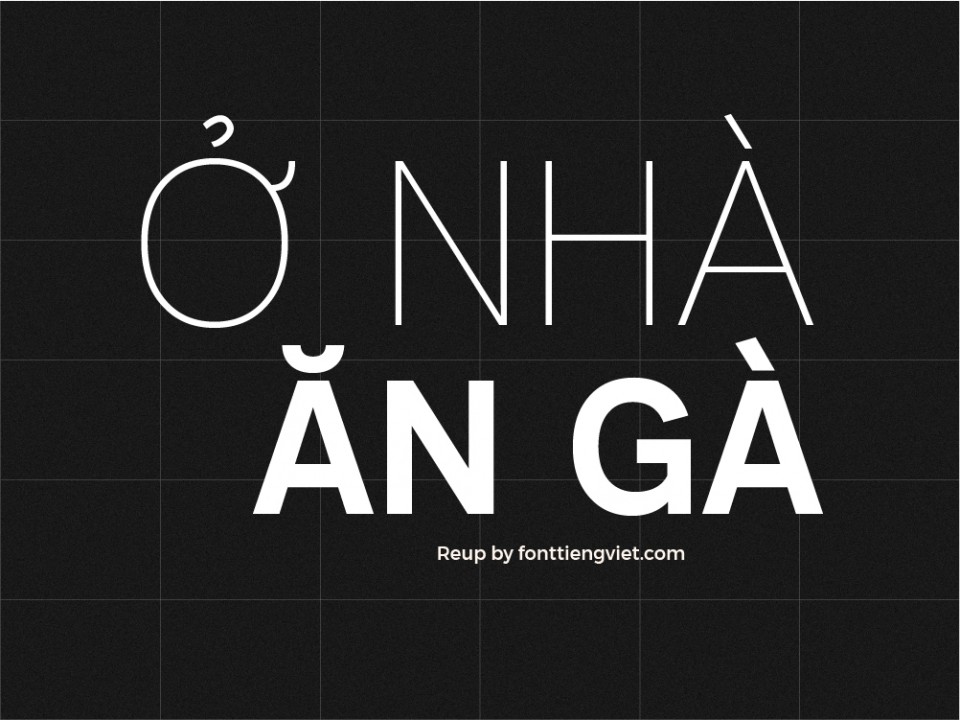
Tải Ngay Bộ Font việt hóa iCiel Novecento ( 6 font ) Sang Trọng Và Đẳng Cấp
Giới thiệu về bộ Font việt hóa iCiel Novecento ( 6 font )
Trong thế giới thiết kế đồ họa hiện đại, việc tìm kiếm một bộ Font Chữ vừa mang nét cổ điển vừa giữ được sự tinh tế là điều không hề dễ dàng. Bộ Font việt hóa iCiel Novecento ( 6 font ) chính là giải pháp hoàn hảo cho các nhà thiết kế tại Việt Nam. Đây là một bộ font thuộc phong cách Uppercase-only (chỉ có chữ hoa), được lấy cảm hứng từ những kiểu chữ hình học phổ biến ở châu Âu vào cuối thế kỷ XIX. Với cấu trúc cân đối và đường nét dứt khoát, bộ font này mang đến hơi thở của sự sang trọng, chuyên nghiệp cho mọi tác phẩm nghệ thuật.
Đặc điểm nổi bật của iCiel Novecento
Bộ Font việt hóa iCiel Novecento ( 6 font ) bao gồm sáu định dạng khác nhau từ Light đến UltraBold. Điều này cho phép người dùng linh hoạt thay đổi độ dày mỏng của chữ để phù hợp với từng mục đích cụ thể như làm tiêu đề sách, bìa tạp chí hay thiết kế logo thương hiệu. Điểm đặc biệt nhất là phiên bản này đã được iCiel Việt hóa hoàn chỉnh, hỗ trợ đầy đủ các dấu tiếng Việt một cách chuẩn xác, giúp các bạn học sinh và giáo viên dễ dàng ứng dụng trong việc trình bày bài giảng hoặc làm poster sự kiện trường học mà không lo lỗi font.
Ứng dụng thực tế của bộ font trong thiết kế
Nhờ tính thẩm mỹ cao, bộ font này thường xuyên xuất hiện trong các dự án quảng cáo cao cấp và thiết kế nhận diện thương hiệu. Sự tối giản nhưng mạnh mẽ của iCiel Novecento giúp truyền tải thông điệp một cách trực diện và ấn tượng. Đối với lĩnh vực giáo dục, bộ chữ giúp các biểu ngữ trở nên trang trọng và hiện đại hơn rất nhiều so với các kiểu chữ truyền thống. Bạn có thể kết hợp chúng với các font chữ không chân khác để tạo nên sự tương phản thú vị và lôi cuốn người xem.
Kết luận về bộ Font việt hóa iCiel Novecento ( 6 font )
Tóm lại, việc sở hữu bộ Font việt hóa iCiel Novecento ( 6 font ) sẽ giúp kho tài nguyên thiết kế của bạn trở nên phong phú và chất lượng hơn. Nếu bạn đang tìm kiếm sự kết hợp giữa nét cổ điển và hiện đại, đừng bỏ qua cơ hội sở hữu bộ Font Miễn Phí, Font Việt Hóa, Font việt hóa iCiel Novecento ( 6 font ) tuyệt vời này để nâng tầm các dự án sáng tạo của mình ngay hôm nay.